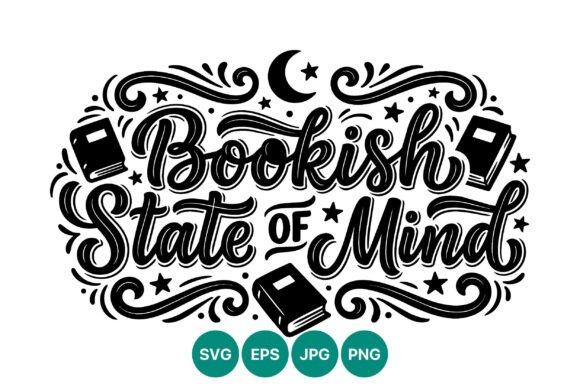
Bookish State of Mind Calligraphic
قد يكون العثور على عناصر التصميم المناسبة أمرًا صعبًا، ولكن Bookish State of Mind Calligraphic يقدم مجموعة استثنائية ترتقي بعملك على الفور.
سواء كنت تقوم بإنشاء منتجات الطباعة عند الطلب أو دعوات الزفاف أو رسومات وسائل التواصل الاجتماعي، فإن Bookish State of Mind Calligraphic هو الخيار المثالي.